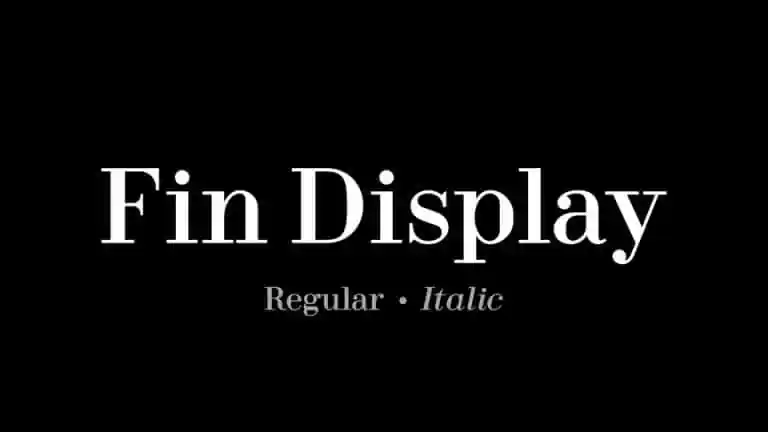
Fin Display Serif Font – Fonte Grátis
Fin Display Serif Font
A Fin Display Serif Font é uma escolha perfeita para quem busca uma tipografia com contraste equilibrado entre as fibras grossas e os travessões finos. Este é um tipo serifizado de alta contraste, disponível nas versões Regular e Italic. Inspirada em Bodoni e outros tipos da era moderna, foi adaptada para melhorar a leitura em dispositivos atuais. Ideal para publicações que requerem elegância e qualidade visual, essa fonte não apenas oferece um estilo elegante, mas também é altamente legível nas telas de hoje, tornando-a uma escolha conveniente tanto para profissionais quanto para designers amadores. Engana-se quem acredita que ser moderno é sempre sobre simplificação. A Fin Display Serif Font combina o melhor da era moderna com elementos serifados clássicos para criar um estilo único e sofisticado, perfeito para qualquer projeto que exija uma aparência envolvente e profissional.